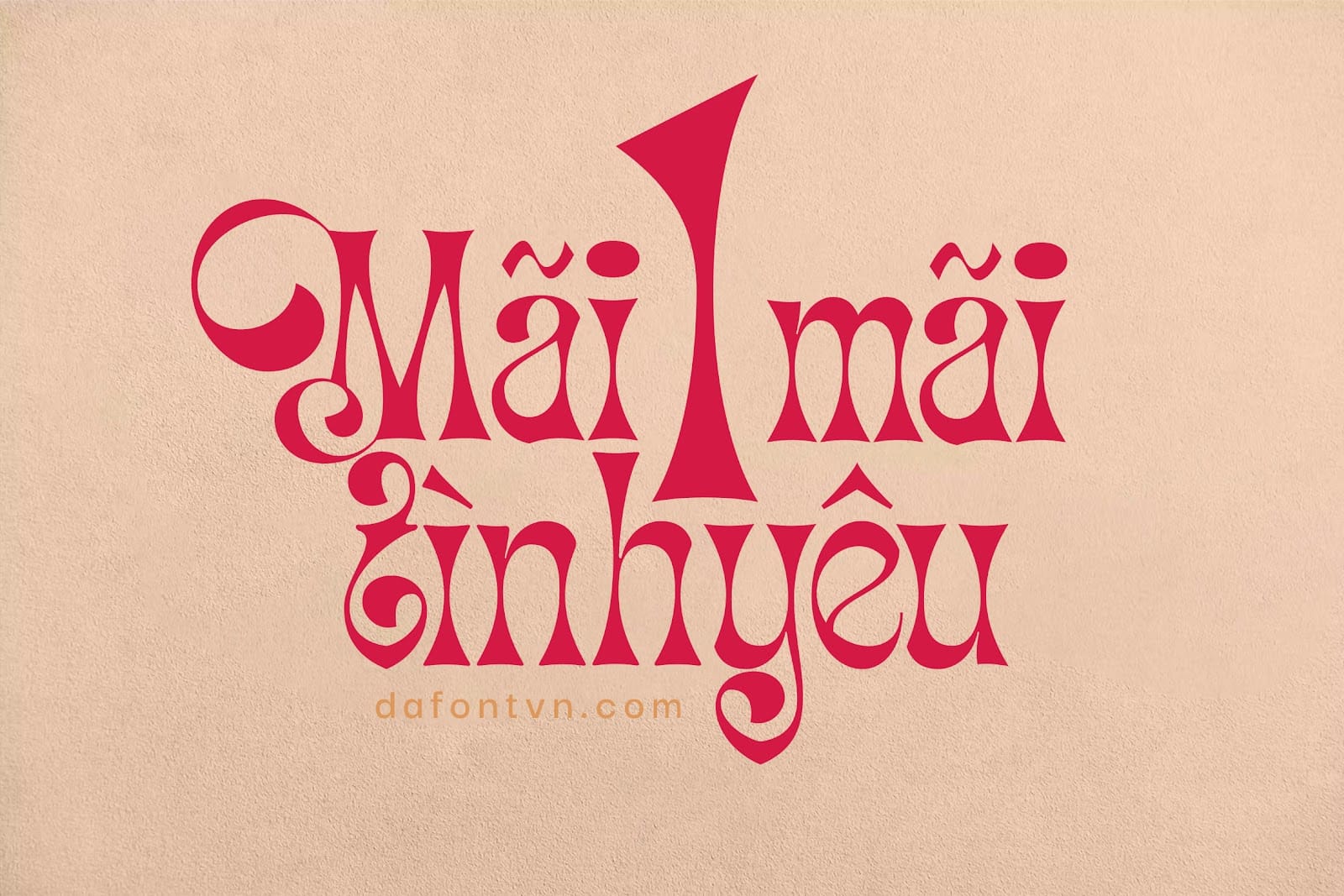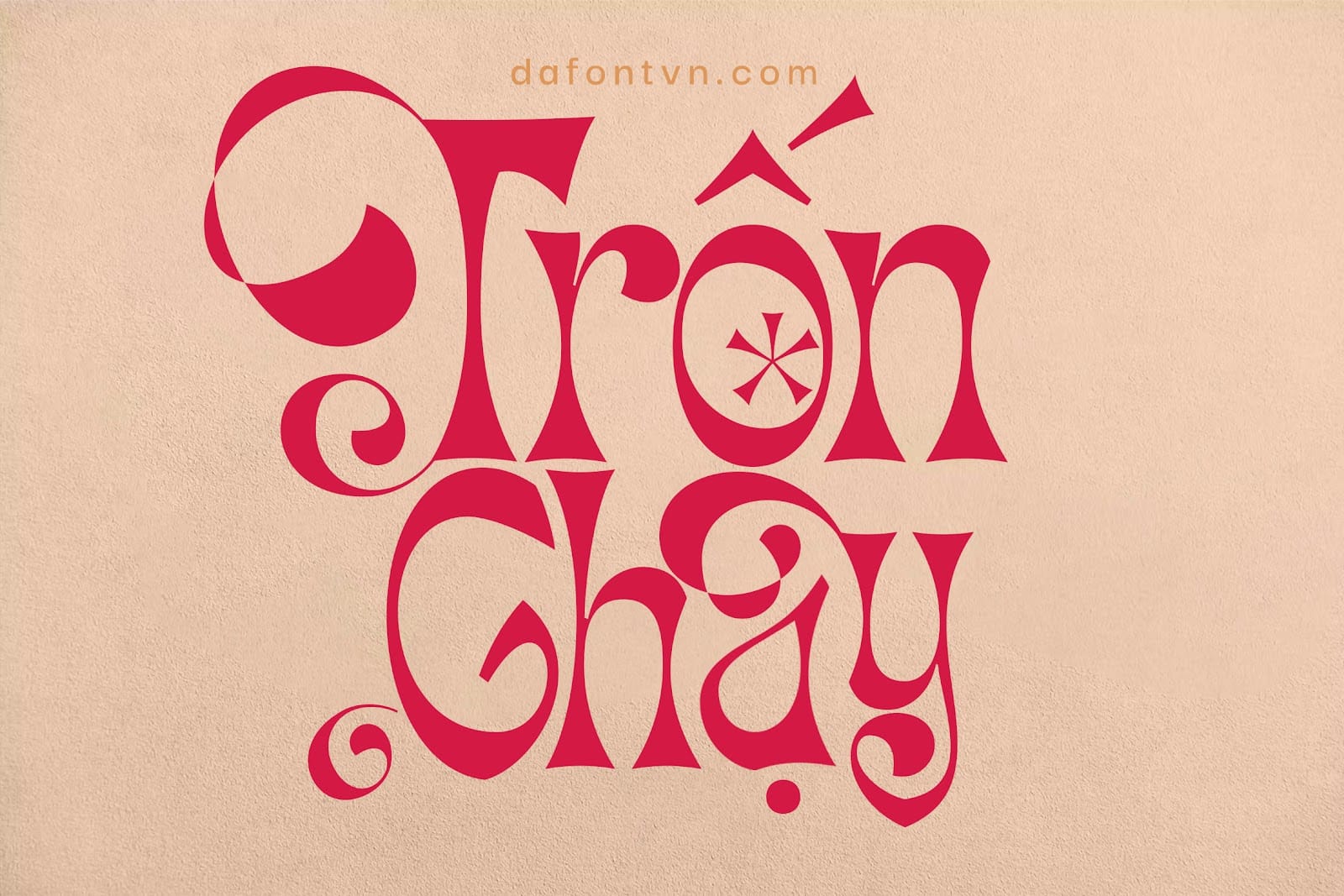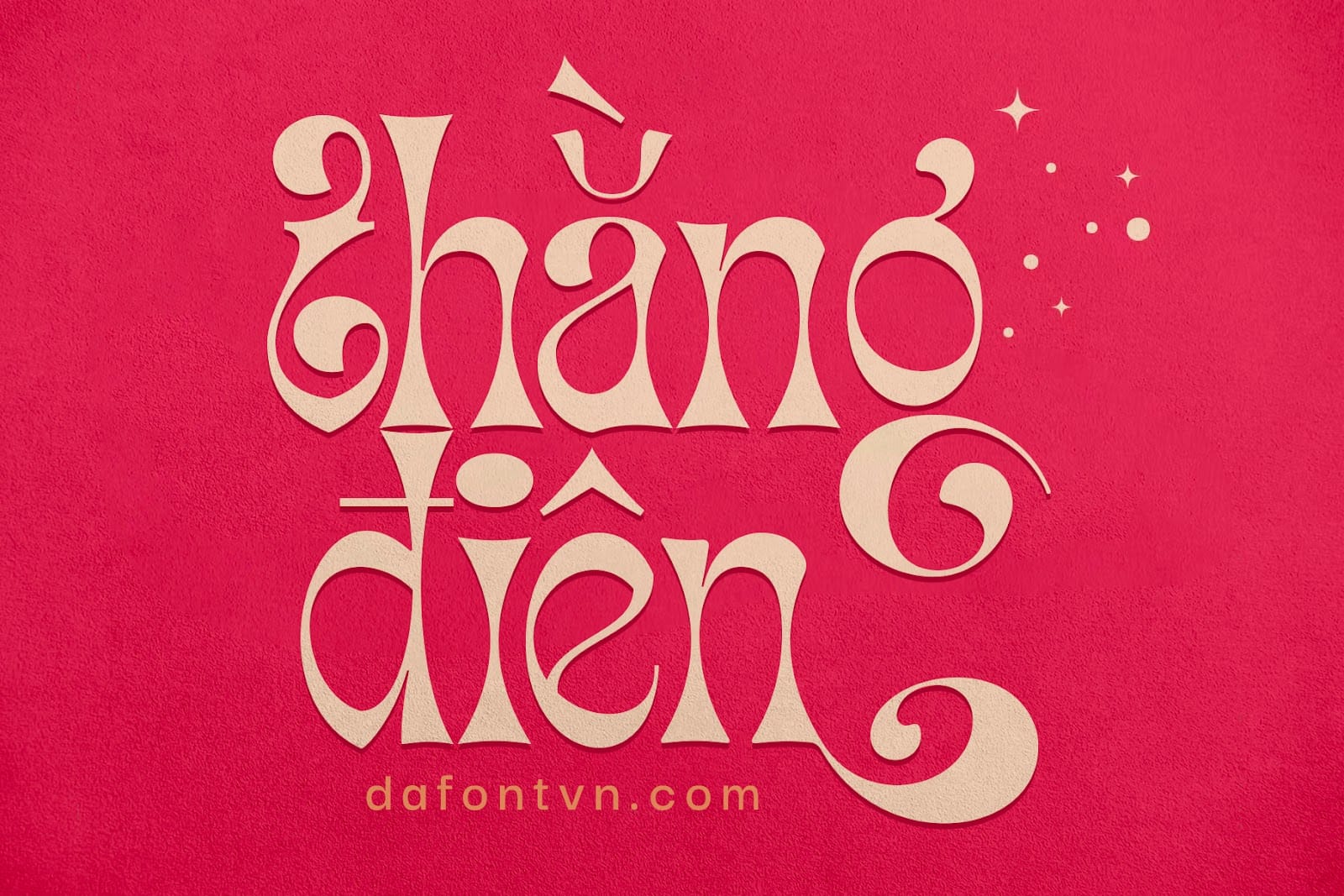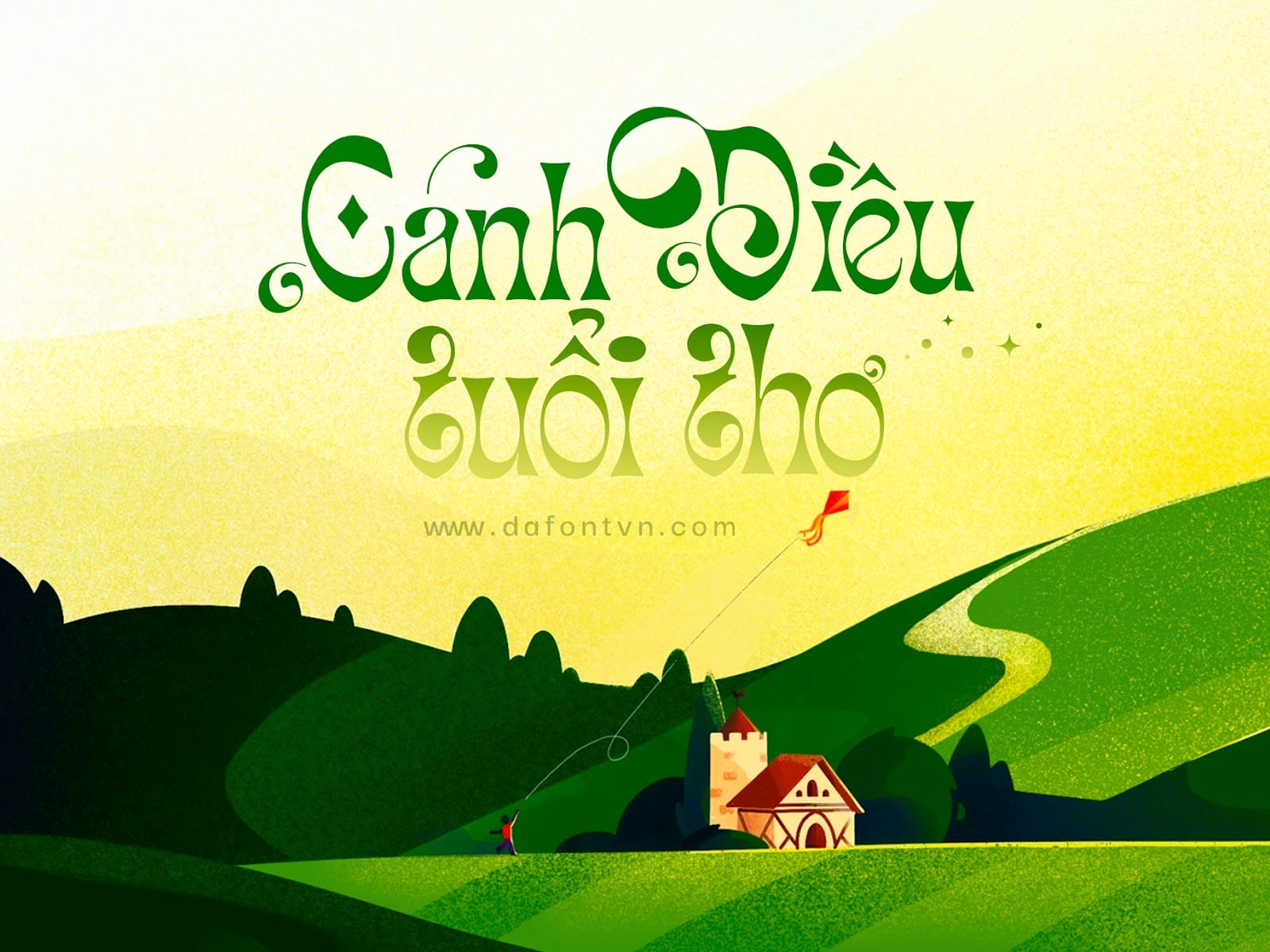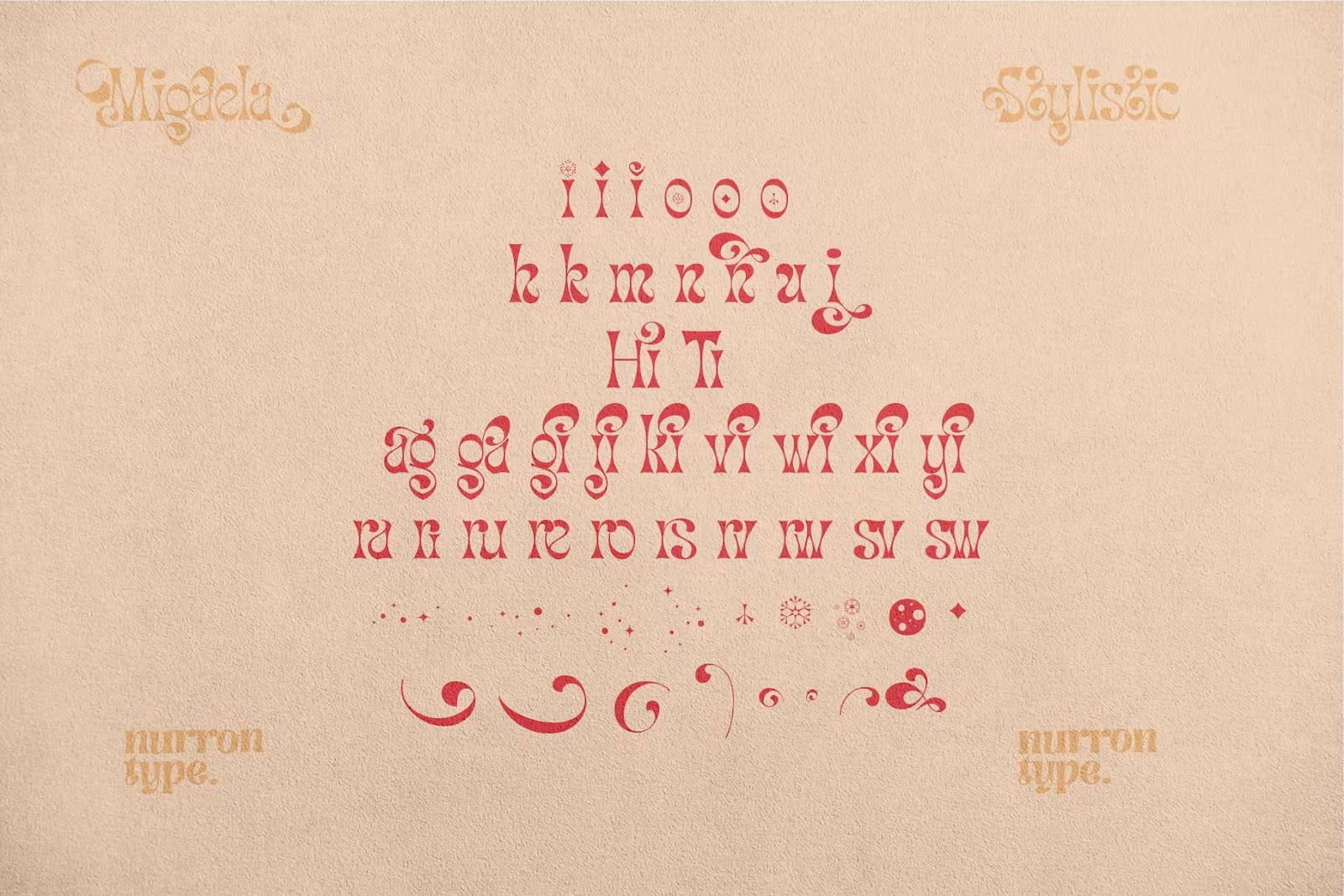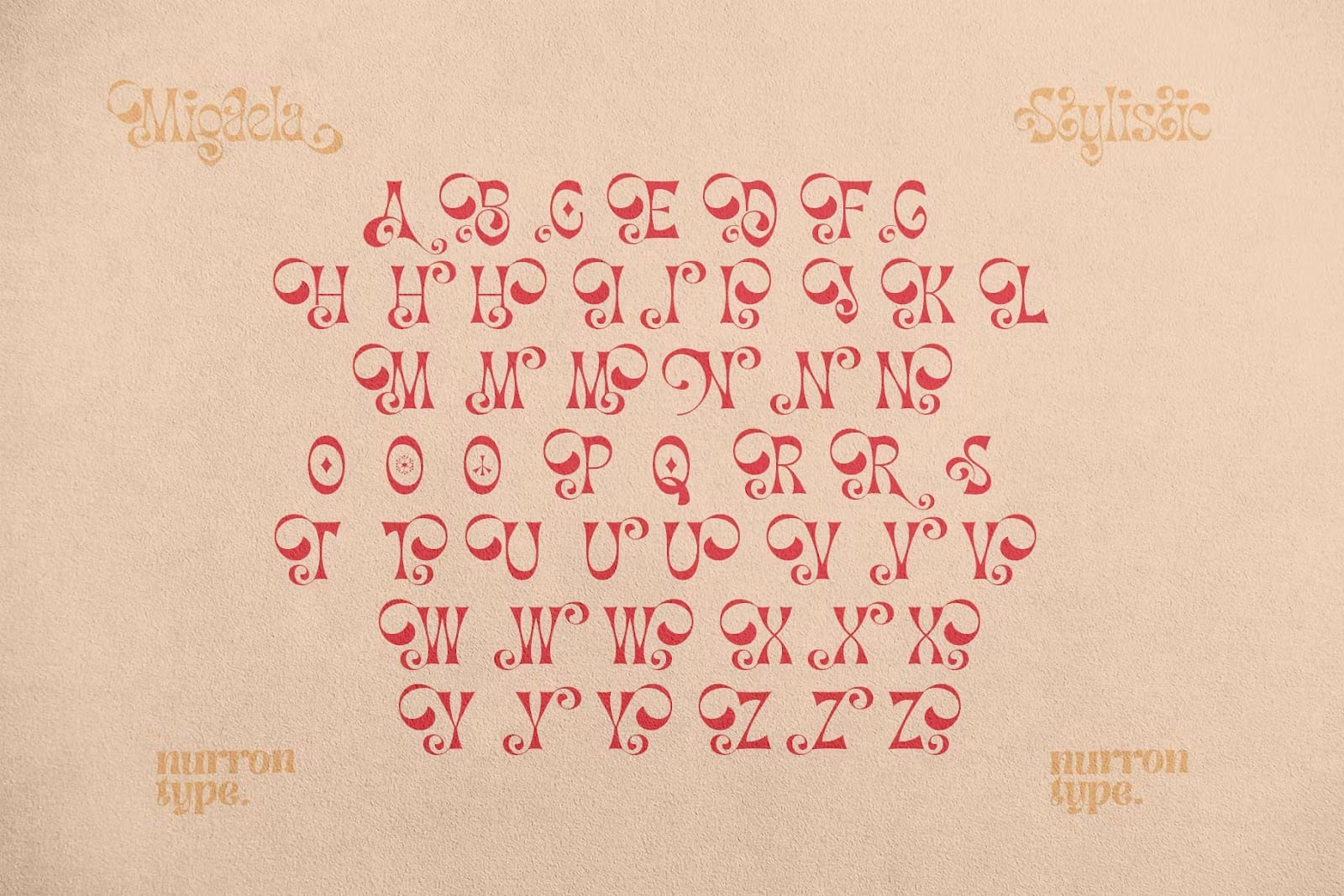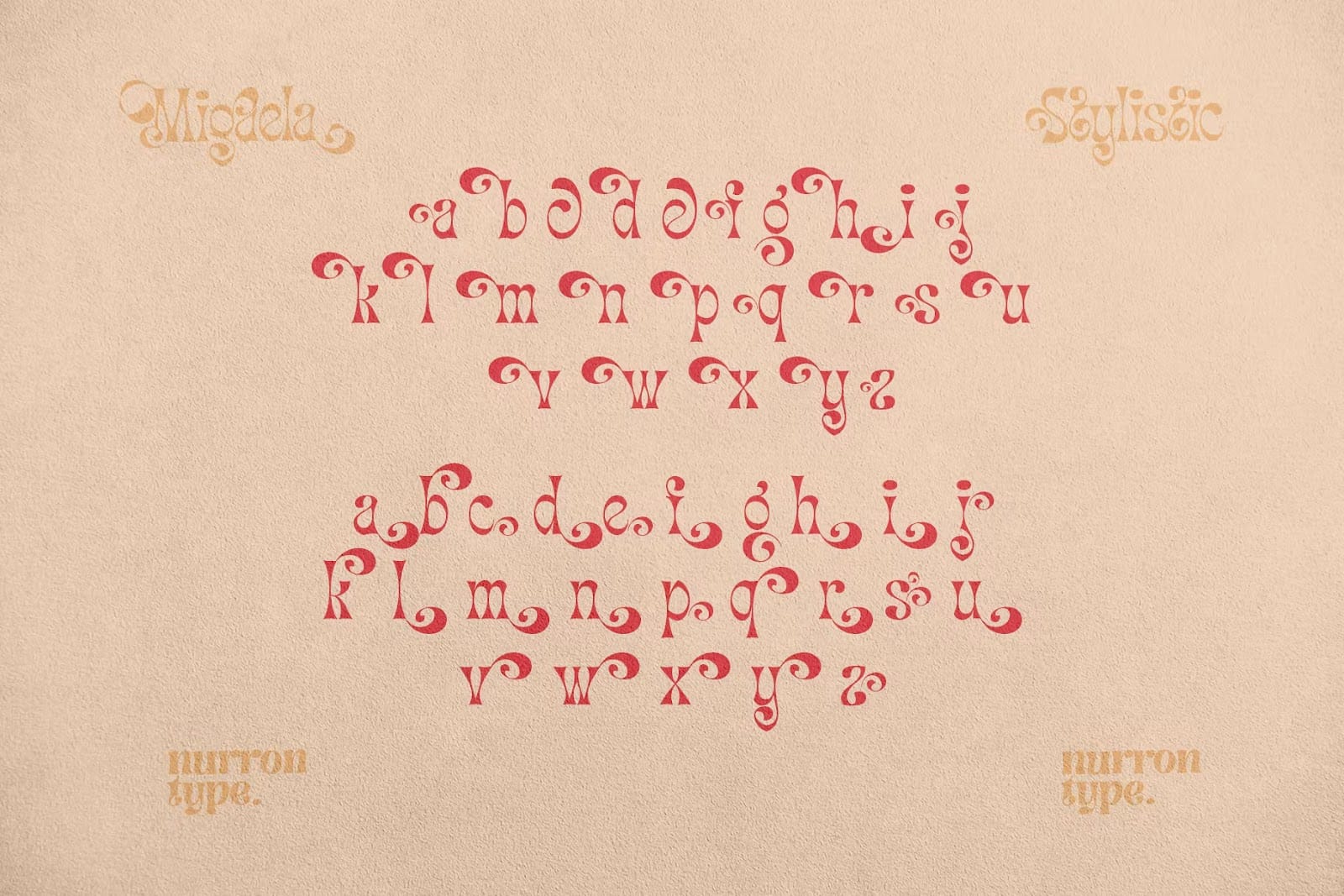
Font việt hóa Migaela – 1 chiếc font xinh xỉu
Xin chào, tôi là Migaela – Tôi là một chiếc font xinh xỉu dành cho bạn đây!Migaela font là một font chữ khá ấn tượng với các đường nét đầy cảm hứng và lạc quan mang phong cách hiện đại và quyến rũ. Bạn có thể sử dụng nó cho bất kỳ các thiết kế nào như dự án Giáng sinh, thiệp mời, sự kiện, typography, quotes…
Ngoài ra font còn đi với hơn 800 glyph cực đẹp khác sẽ đem đến cho bạn những kết hợp hoàn hảo để tạo ra những tác phẩm thiết kế thật ấn tượng và độc lạ.
Font có 3 kiểu (Regular, Overlap và Smooth) và đã được việt hóa đầy đủ cả 3 kiểu, một số dấu và ký tự được chỉnh sửa lại cũng như căn chỉnh hoàn hảo nhất.